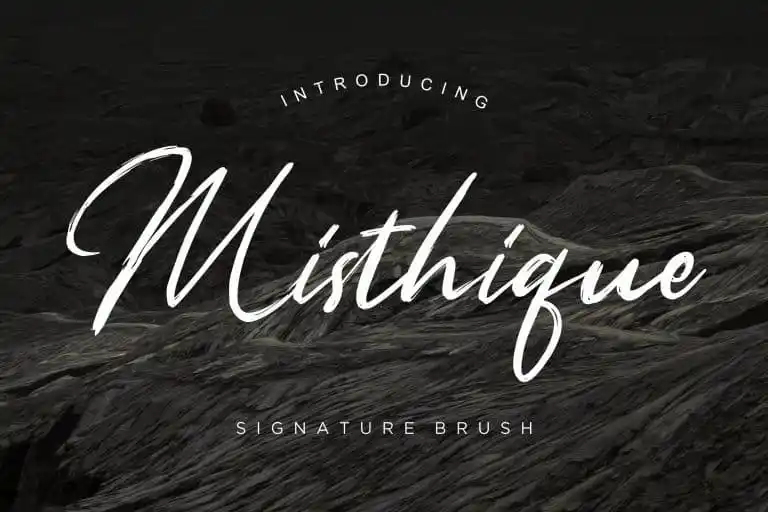
Misthique Brush Font – Download Grátis
A Misthique Brush Font é uma elegante fonte cursiva criada pela Creatype Studio para quem busca adicionar um toque único à suas criações digitais. Esta fonte foi projetada com características que fazem-a parecer perfeita para diversos tipos de trabalhos gráficos, como o design de logomarcas, embalagens de produtos e até mesmo na edição de fotos. Perfumando-se com uma textura elegante e suavizada, a Misthique Brush Font é ideal tanto para projetos que exigem um ar artesanal quanto para aquelas necessidades que buscam um estilo mais contemporâneo. Seja criando um design de produto luxuoso ou preparando um post de rede social com o charme delicado do traçado manual, a Misthique Brush é uma escolha inegável. Adotada em designs para blogs, produtos de moda e até mesmo em trabalhos publicitários, esta fonte traz ao design tanto funcionalidade quanto originalidade. Sua versão script não apenas torna o texto mais interessante, mas também adiciona um toque pessoal que é tão importante em um projeto visual. Com sua presença harmoniosa nas diversas categorias de trabalho gráfico onde se aplique, a Misthique Brush está certamente entre as melhores fontes cursivas disponíveis para quem busca uma combinação perfeita de estilo e funcionalidade.